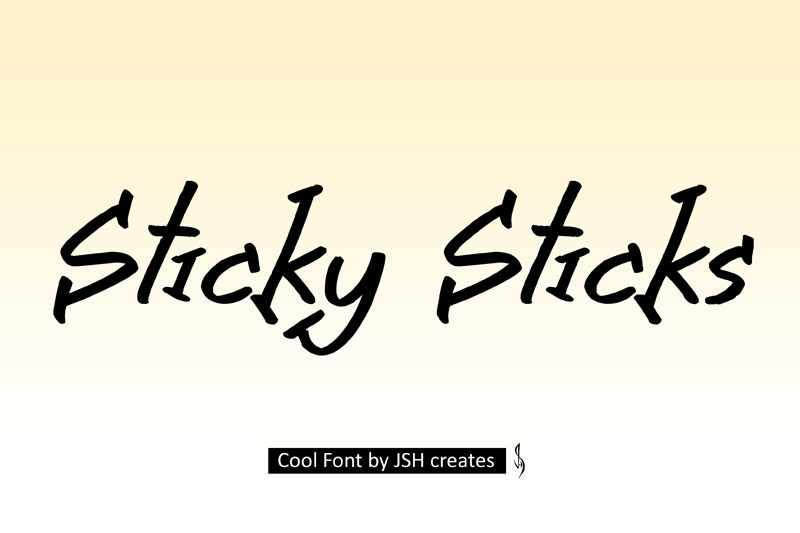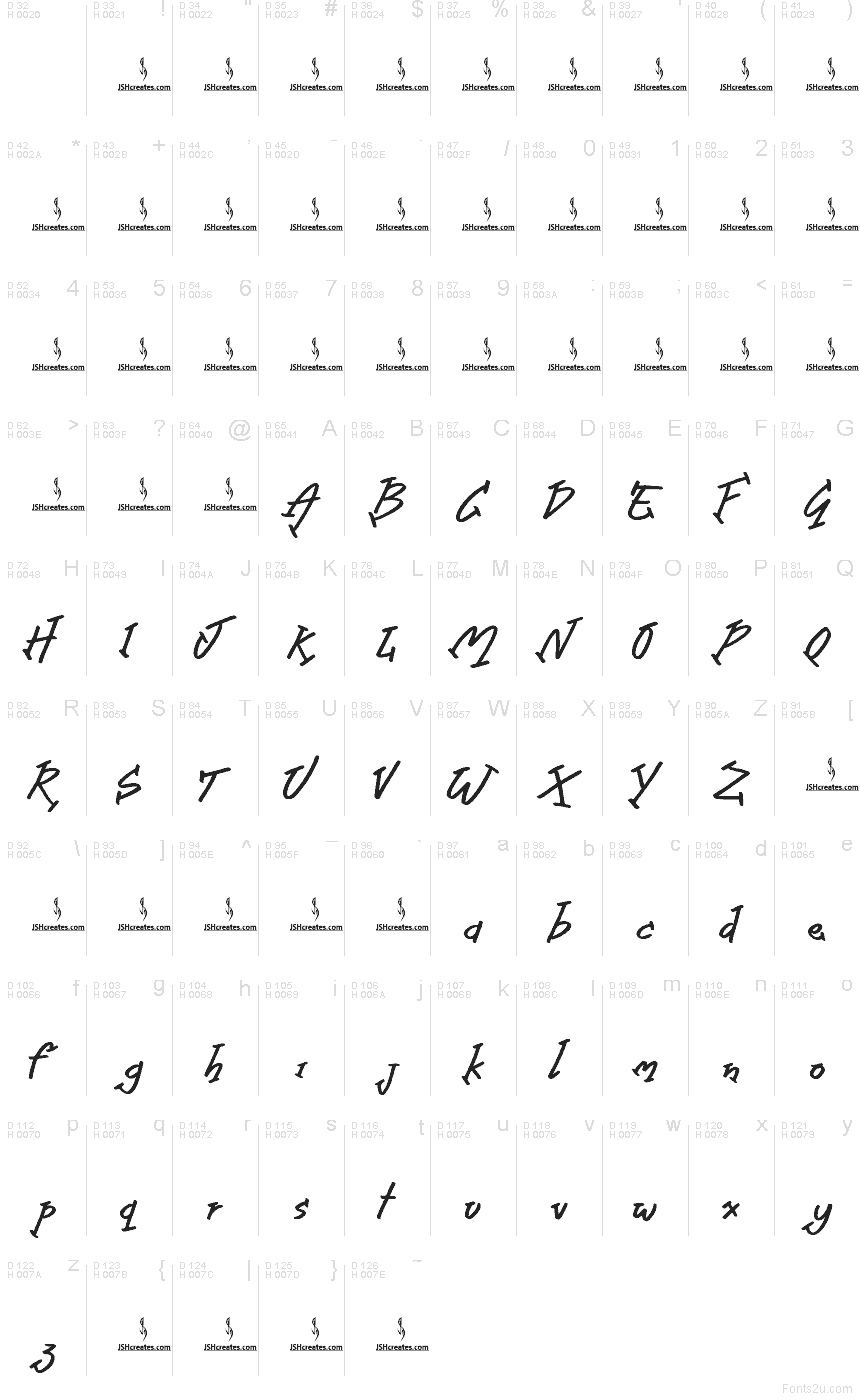
Sticky Sticks
Sticky Sticks — это бесплатный мультяшный акцидентный шрифт, передающий непринужденную энергию надписей, сделанных маркером в скетчбуке. Буквы наклоняются и «дрожат» благодаря неровным штрихам, острым концам и слегка хаотичному ритму, что делает шрифт игривым, а не выверенным до идеала.
Это отличный выбор для обложек комиксов, детской упаковки, школьных плакатов, приглашений на вечеринки и быстрой графики для соцсетей, где бесплатный шрифт должен выглядеть неформально и «по-домашнему». Он также хорошо подходит для коротких заголовков: прыгающая строка и грубая кистевая отделка придают даже паре слов живой, нарисованный от руки характер.